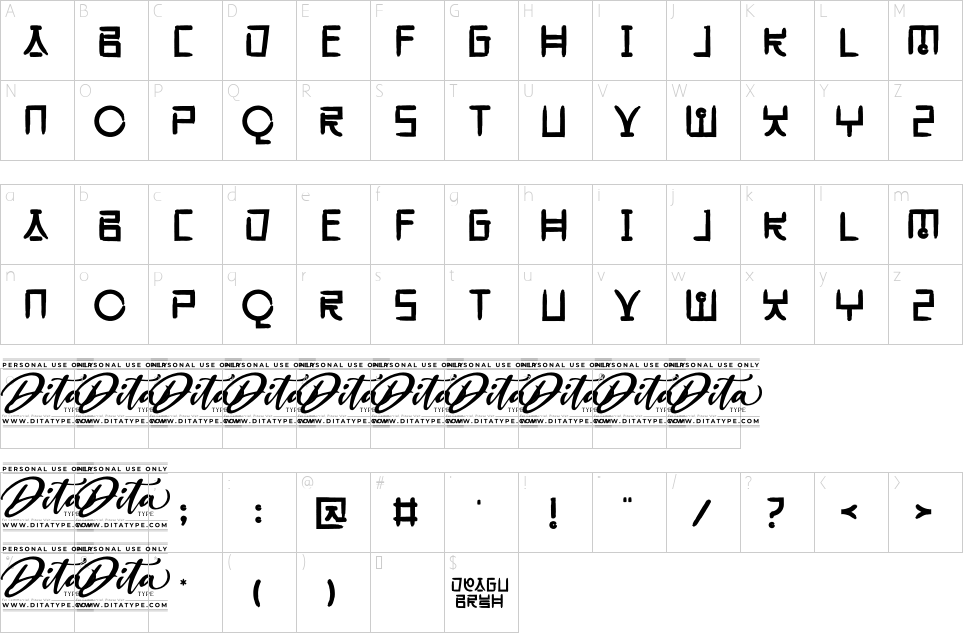
Deagu Brush Font – Download Grátis
Descubra a essência das letras com Deagu Brush Font. Essa bela fonte foi cuidadosamente criada pela Dita Type, ideal para quem busca uma paleta de opções que se destaca na comunicação digital e impressa. Com seu traço delicado e textura suave, Deagu Brush é perfeito para destacar mensagens importantes ou adicionar um toque artesanal a qualquer projeto gráfico. Sua elegância e versatilidade a tornam uma escolha inteligente para designers e profissionais do design que buscam não apenas fontes bonitas, mas também fontes comuns de alta qualidade disponíveis gratuitamente. Se você está procurando por uma opção única e sofisticada para seus projetos, Deagu Brush Font é o recurso gráfico perfeito para você. Sua versão gratuita permite explorar as capacidades únicas desta fonte delicada que enriquece seu design com um toque de arte refinada.